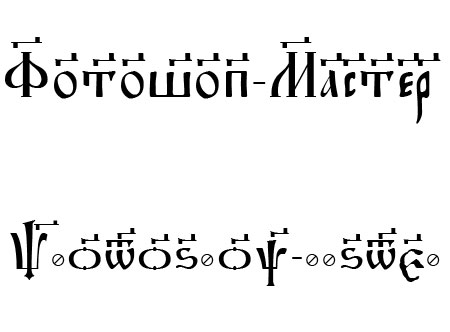
а их можно же убрать
лехко и просто
просто пирёш и пишеш что нибуть
потом выбираеш инст. кисть
потом там вылезет окошко там нажми да
потом возьми стёрку и стери =)
Всё бы хорошо, но эти чёрточки вверху, всё портят...